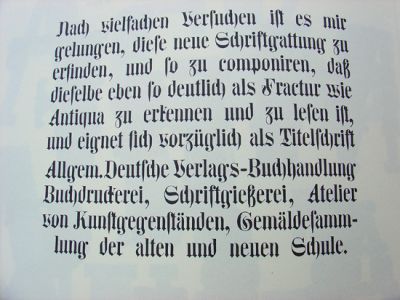
Hier die Auflösung:
Normal, Berlin, Tuch, Ruf und Nil war ja schon gut und hätte manchen Schriftsteller zu Höchstleistungen getrieben, aber hier kommt:
ALARM!
und wann ist bitte das Entstehungsjahr?
Ich bin zwar nicht Schmorkohl aber hier kommen die Daten zur Schrift:
Entwerfer: Heinz König, Entstehungsjahr: 1928 in normal in den Größen 8 –84 Pkt, und als Plakatschrift 10 – 24 Cicero.
Ich wußte doch, daß ich die Schrift kenne …
die Alarm ist ein Auszug aus dem Schriftmuster der
Hauptprobe J. D. Trennert & Sohn, Altona Elbe, gegründet 1634.
Das Vorwort ist geschrieben, im Januar 1930.
Die Alarm ist »eine erstklassige Schriftschöpfung des bekannten Künstlers Heinz König
/ Lüneburg / Original / Erzeugnis
unseres Hauses J. D. Trennert & Sohn, Altona / Schrifgießerei«
Ich hatte beim Durchschauen und der Auswahl der Origami bzw. der Kompakt einfach die gleiche Idee …
PS: Ich kann das zur Mode gewordene
rumquängeln an der DIN-Einordnung nicht
mehr hören, hier bin ich aber ganz unschlüssig
und frage schüchtern: Antiqua-Variante,
leicht angebrochen?
Meines Erchtens, ist die DIN eine sehr gute Klassifikationsmatrix, da sie die Schriften versucht historisch in chronologischer Folge zu ordnen, und somit einen kleinen Teil zum kunsthistorischem Allgemeinwissen beitrgägt. Durch die DIN weiss jeder der sich mit ihr beschäftigt, wie eine Antiqua während des Barock oder während des Klassiszismus ausgesehen hat, und in welcher Reihenfolge die Schriften entstanden sind. Dass in ihr die Bastarda nicht enthalten ist, ist nicht wirklich ein Kritikpunkt von mir gewesen. Die DIN ist halt für den deutschen Gebrauch angepast worden, also reicht es auch vollkommen aus, wenn nur die Schwabacher in ihr vetreten ist.
hattest du eigentlich schön die Lösung genannt, wie die Schrift auf dem letzten Bild von dir heißt!? Oder hab ich das irgendwie überlesen?
Meines Erachtens handelt es sich um die Centralschrift http://www.beepworld.de/members66/vau-ef-be/weiteres.htm
Es gibt auch einen Font von Harold's Fonts (Kombine) in regular und kursiv, der aber nicht ganz mit dem Original übereinstimmt:
Rudolf Bosshardt hat irgendwo – fällt mir wieder ein – einmal eine ganze Reihe solcher Hybrid-Experimente vorgestellt, die, wenn ich mich recht erinnere, allesamt aus der Zeit vor ca. 1920 stammten.
»Meines Erachtens handelt es sich um die Centralschrift ...«
»Also war so was gar nicht originell?
https://www.myfonts.com/fonts/volcano/fraktendon/ ...«
»... allesamt aus der Zeit vor ca. 1920 stammten.«
Ihr werdet mir unheimlich, alles richtig, unglaublich!
Schön auch, daß man sich selber gar nicht melden muß,
›Mischschrift‹
sogenannte Centralschrift, Schriftprobe der Gießerei C. G. Schoppe.
Berlin 1853
An Steven Wulf: Ich mag die DIN 16518, Deinen Beitrag würde ich so
»I« ist es leider auch nicht.
I ist gleich J minus Q somit bleiben (Grafiker-Hirn streng dich jetzt bitte an!),
dreiunzwanzig von sechsundzwanzig.
Hier noch das Zusatzzahl-»I«.